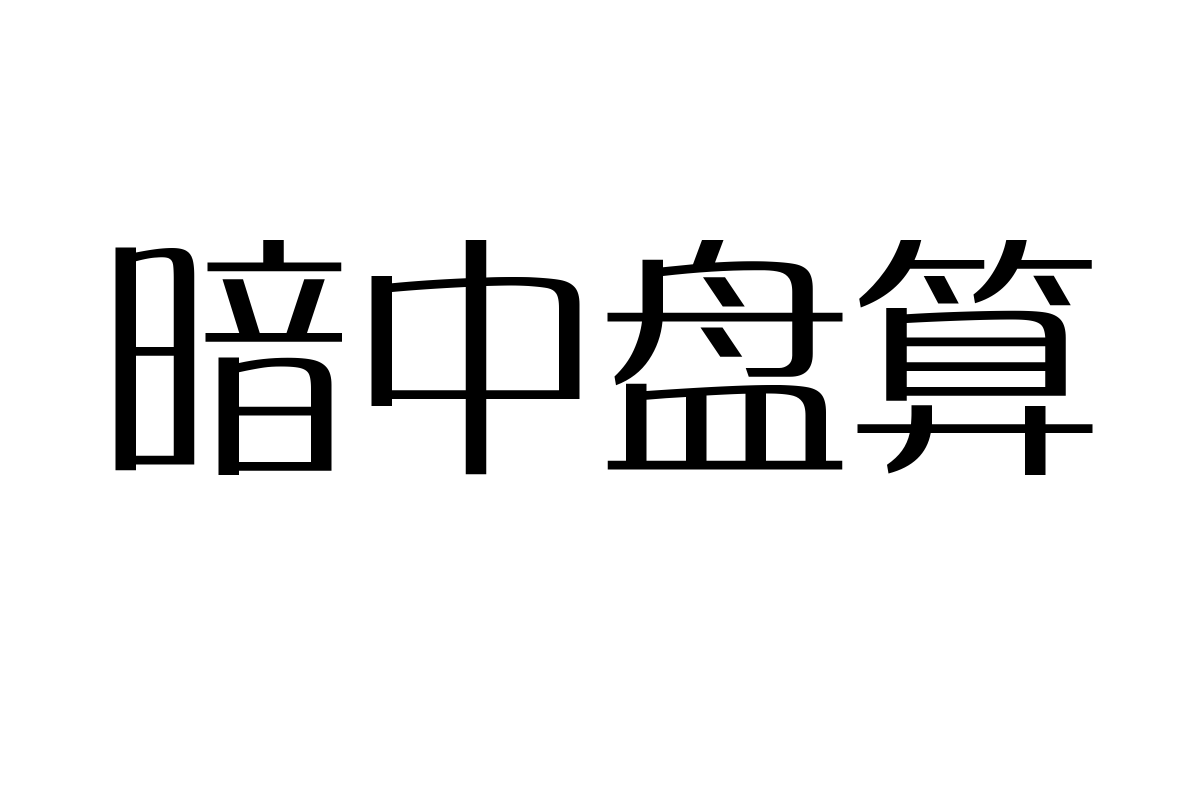
三极智黑体是一种具有独特风格的中文字体,它由北京华文彩云科技有限公司设计。这款字体以其独特的字形设计和丰富的笔画变化而受到广泛好评。
三极智黑体的字形结构紧凑,笔画清晰,给人一种简洁明快的感觉。它的笔画粗细适中,既有力度又有美感,适合用于各种需要突出文字的场合。此外,三极智黑体的字形也具有一定的可读性,即使在不同字体大小下也能保持清晰的视觉效果。
除了美观大方的特点外,三极智黑体还具有较强的适应性。无论是在电脑屏幕上还是在手机上,都能展现出良好的视觉效果。同时,这款字体也具有较高的识别度,有助于提高品牌识别度和视觉冲击力。
总之,三极智黑体是一款非常优秀的中文字体,无论是在商业广告、企业标识还是其他需要突出文字的场合,都值得一试。